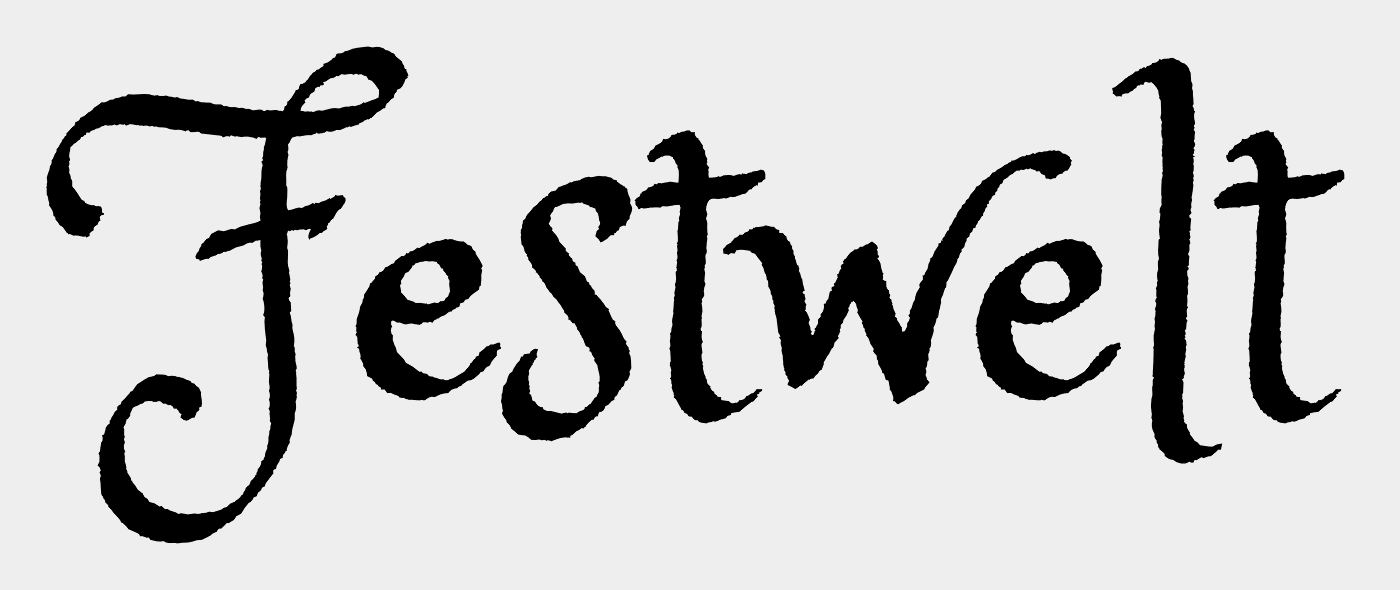
Logoschrift gesucht, erstellt von Grafiker
ich habe mein Logo von einem Grafiker erstellen lassen, der leider nicht sehr auskunftbereit ist. Ich benötige die Schrift aber für diverse Gestaltungen, Flyer & Co.
Kann mir jemand sagen, welche Font "Festwelt" ist? Eine ähnliche Schrift würde mir auch reichen, das Logo wird eh nochmal überarbeitet....
Es muss eine Satzschrift sein, das habe ich schon durch  das Ausschlussverfahren fest gestellt.  Gleiche Buchstaben, eine Grundlinie...